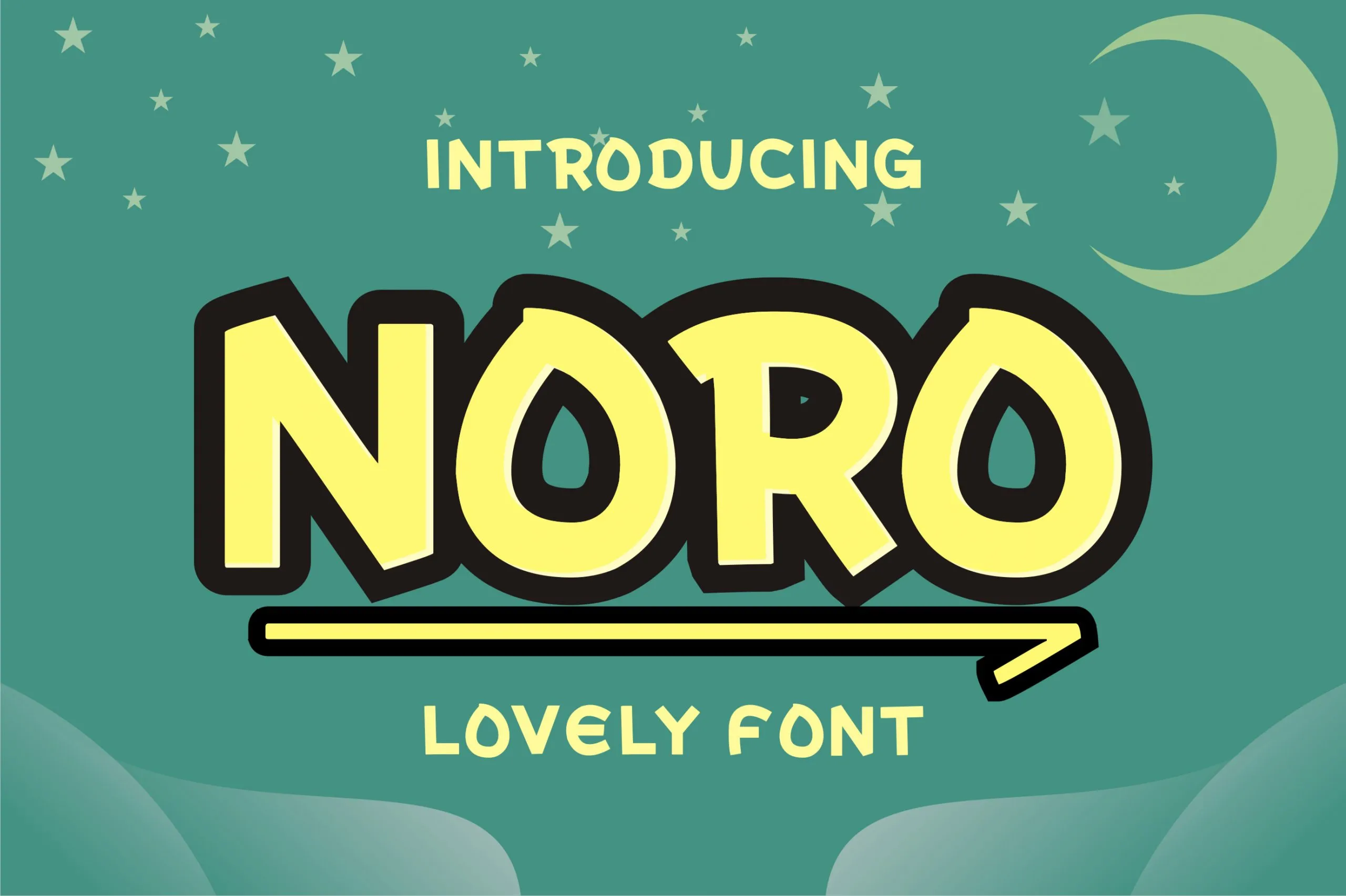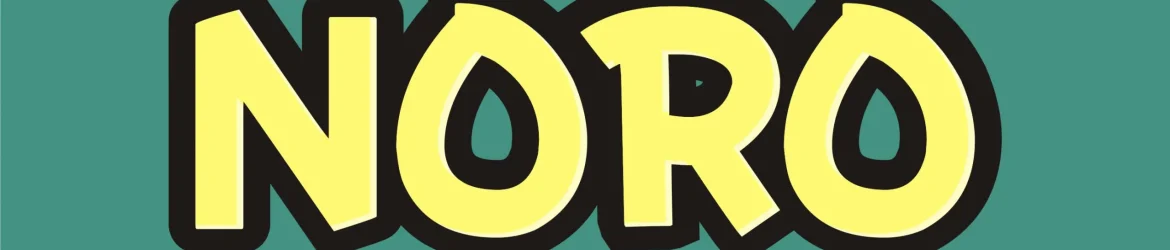
Noro Font – Download Grátis
Esta é uma fonte tipo display leve chamada Noro. Ela combina elementos espessados e adaptáveis para projetos visuais interessantes. Especificamente, esta fonte contém caracteres Unicode Personal Use Area (PUA) que permite você acessar facilmente todas as linhas de estilo e acordes com uma simples manipulação dos teclados. Noro é perfeita para aplicativos infantis, especialmente quando combinado com cores vistosas e vivas. Perfect para tornar qualquer projeto atraente e divertido para crianças. Letterfiastudio criou essa fonte exibindo grande versatilidade em um estilo tipográfico despojado e divertido.